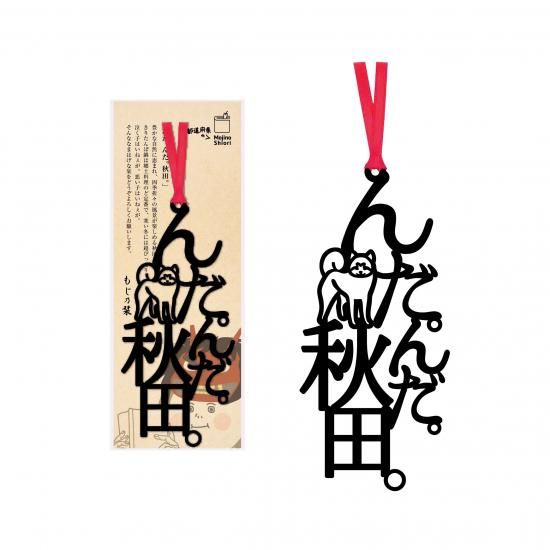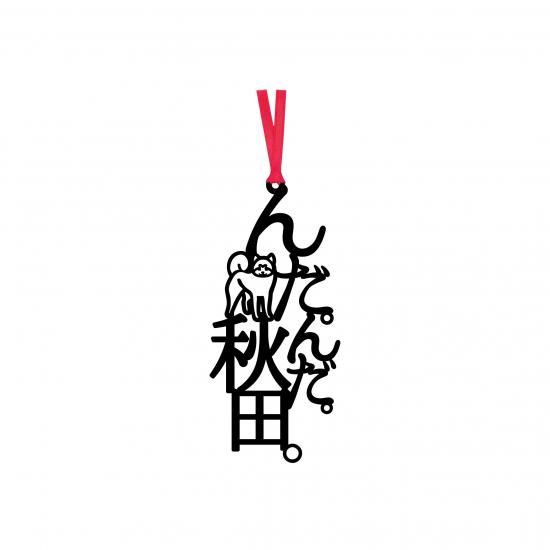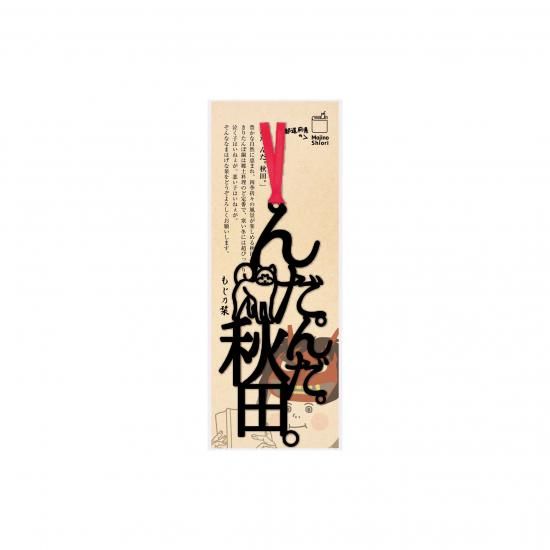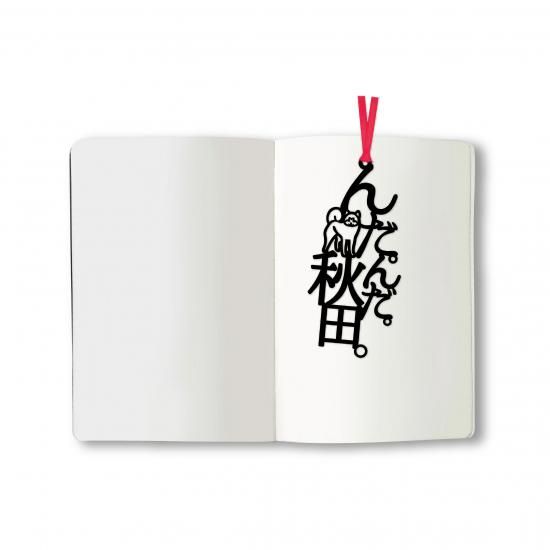
文字の47都道府県のしおり「んだ。んだ。秋田。」
豊かな自然に恵まれ、四季折々の風景が楽しめる秋田。
きりたんぽ鍋は郷土料理のど定番で、寒い冬には超ぴったり。
泣く子はいねぇが。悪い子はいねぇが。
そんななまはげな栞をどうぞよろしくお願いします。
木材パルプや綿を原料とした環境素材を採用し、耐久性・耐水性に優れたファイバーの特徴を活かすことで、言葉がフォントごと切り取られたような巧緻で美しい『文字のしおり』のデザインが実現しています。